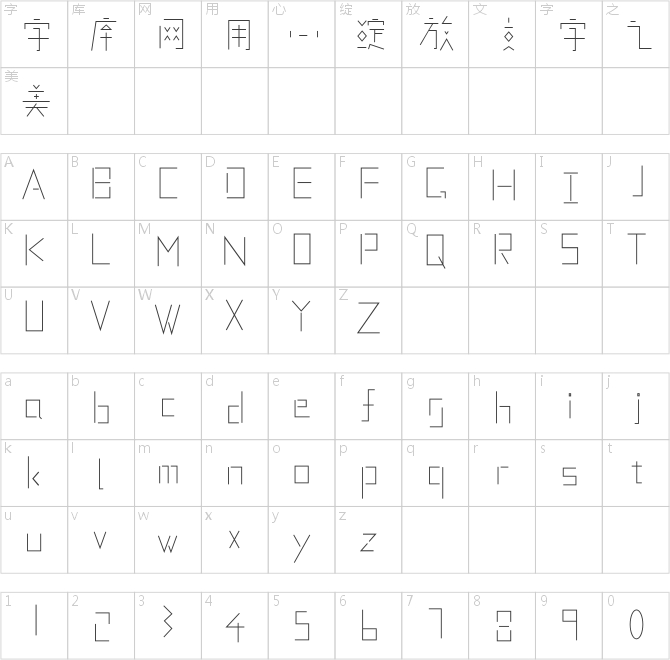
字體名稱: 佛君城建體
佛君城建體
佛君城建體介紹
作品以線條為緣起,以抽象幾何手法,構筑極簡唯美的城市建筑意象,除橫平豎直的基礎表現,融入45度斜角展開的線條,在保證識別性的基礎上減化筆畫,歸納出易于表現為幾何造型的結構,形成結構獨特、識別效果突出、極具時尚感的字型,契合互聯網時代個性鮮明的傳達需求,提供獨具一格的視覺傳播解決方案。